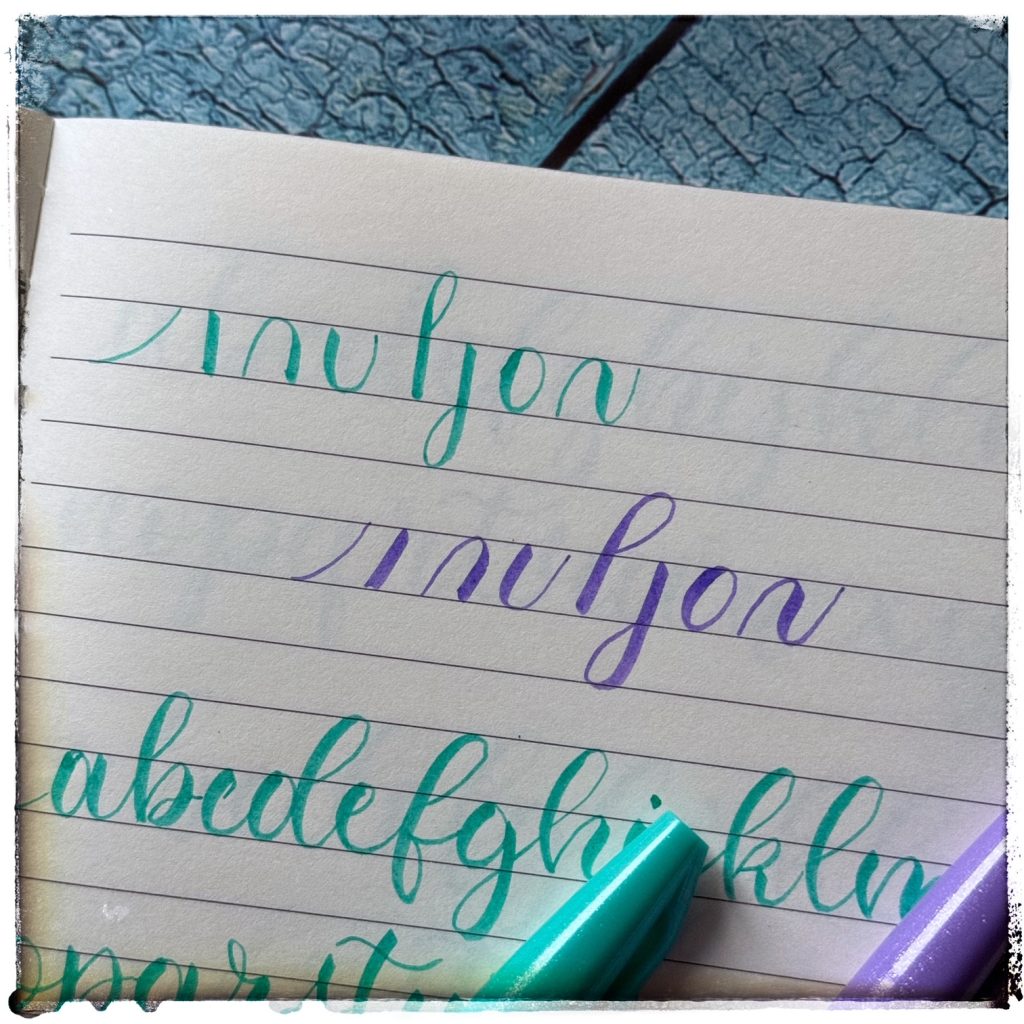
Modern kalligráfia
Leggyakrabban a modern kalligráfiával találkozhatsz a közösségi médiában, mutatom, hogy mit érdemes ismerned róla, hogyan tudod elsajátítani.
modern kalligráfia abc
Sokat gondolkoztam, hogy írjak-e a modern kalligráfiáról, mert igazából ez nem olyan, mint a Copperplate, Spencerian, gótikus vagy még sorolhatnám tovább a stílusokat, nincs egy etalon belőle. Ha beírod a keresőbe számos képet dob ki, amelyek első ránézésre nagyon hasonlóak, de ha közelebbről megnézed mindegyik kicsit más. Elmesélem, hogy én hogyan alakítottam ki a saját modern kalligráfia stílusomat, és ennek segítségével hogyan találhatsz rá te is a magadéra.
Szabályok, amik mentén ki tudod alakítani a kalligráfia stílusodat
Most még is vannak szabályok, kérdezhetnéd, hiszen az előbb azt írtam, hogy ez egy kötetlenebb stílus. Van néhány útmutatás, amit érdemes figyelembe venni, mert így tudod egységessé tenni az írásképet.
Az egyik legalapvetőbb szabály, hogy ha felfelé húzzuk a vonalat, akkor vékony, ha lefelé, akkor vastag. Ez így nagyon könnyűnek hangzik, meg olyan semmitmondónak is, szóval ugorjunk is a következő iránymutatásra.
Itt is minden az alapvonásokon múlik, ugyanúgy meg van ennél a stílusnál a szokásos vonás sor (kezdő vonás, felfelé és lefelé mutató görbe stb.). Ebből a szempontból nagyon hasonlít a Copperplate stílusra, azonban itt simán választhatod azt, hogy a betűk egyenesen állnak, vagy nem pont 55 fokos szögben döntve. Igazából te döntöd el, hogy melyik tetszik jobban. Egy dologra figyelj, ha az egyenes mellett döntöttél, akkor onnantól csak úgy írj, párhuzamosak legyenek a betűid, ha ferde betűk mellett tetted le a voksodat, akkor azt kövesd.
modern kalligráfia alapvonások
A következő döntési pont, hogy milyen magasságúak legyenek a betűk. Itt is általában oválisban szoktunk mérni, azt tapasztaltam, hogy itt az 1:1:1 arány jön be. Az az a hurkok és a betűtest egyforma nagyságúak. Azonban ez rád van bízva, döntsd el, hogy mi tetszik, de tudod csak úgy, mint a dőlésnél itt is legyél konzekvens, ha egyszer magasabb vagy alacsonyabb hurkok mellett döntöttél, akkor végig azt használd.
Néhány hasonlóság, ha a betűket megnézed az o betűnél általában mindenki a hurkos verziót használja, amit nálam is látsz a képen. A b és p betűnél is ez az áthurkolt pocak a jellemző, illetve a t betűt hullámosan húzzuk át, nem pedig egy rövid egyenessel. A d betűnél pedig általában a szár egy l-hez hasonlít.
Hogyan is állj neki?
Ok, szóval már tudod mire kell figyelni. Jöhet az inspiráció, nézz körül az instán vagy a pinteresten, és találd meg melyik stílus tetszik. Előfordulhat, hogy csak 1-1 elemet veszel át, nem az egészet. Fontos, hogy először az alapvonásokkal kezd. Próbáld meg megtalálni az adott stílusnak az alapvonásait. Ez, ha kezdő vagy rémisztőnek tűnhet, ezért is javaslom, hogy elsőre kezdj egy Copperplate stílussal, mert, akkor megérted a logikáját, és abból tudsz építkezni.
Utána jöhet a gyakorlás, először az alapvonásokat, hogy azokkal kapcsolatban alakuljon ki az izommemória, utána kezd el összeállítani a betűket, betűkapcsolatokat, majd jöhetnek a szavak és a mondatok, idézetek. Aztán már ha éjszaka felkelsz az álmodból, akkor is tudod, hogyan kell írni a bármit is.
Milyen eszközöket használj a modern kalligráfiához?
Erről is írtam korábban, hogy milyen eszközöket ajánlok. Így most csak röviden összefoglalom. A legegyszerűbb az ecsetfilc, abból is szerintem érdemes a kis ecsetfilcet használni. A kedvenc márkáim Tombow Fudenosuke vagy a Pentel Touch Sign. A képeken ez utóbbit látod.
Ha papír, akkor Rhodia pad, a modernhez sokszor ajánlják a kockásat vagy hivatalosan a négyzethálósat. Azért jó állítólag, mert így könnyebben el tudod sajátítani, hogy egységes legyen a stílus. Nekem túl sok a vonal benne, inkább a pöttyöset szeretem, ha kezdő vagy érdemes kicsit bevonalazni. Aztán a nagy kedvencem a Canson XL marker, mert átlátszó és bármilyen gyakorlólapot alá tudok tenni.
Ha további íróeszköz, akkor választhatod még a mártogatós tollat, de egy sima ceruzával is elkezdheted a gyakorlást, azzal is simán tudsz vékony és vastag vonalakat húzni, ha puhább fajta. Az insta oldalamon találsz rá példát, ahol megmutatom, milyen menő, gyere és nézd meg!